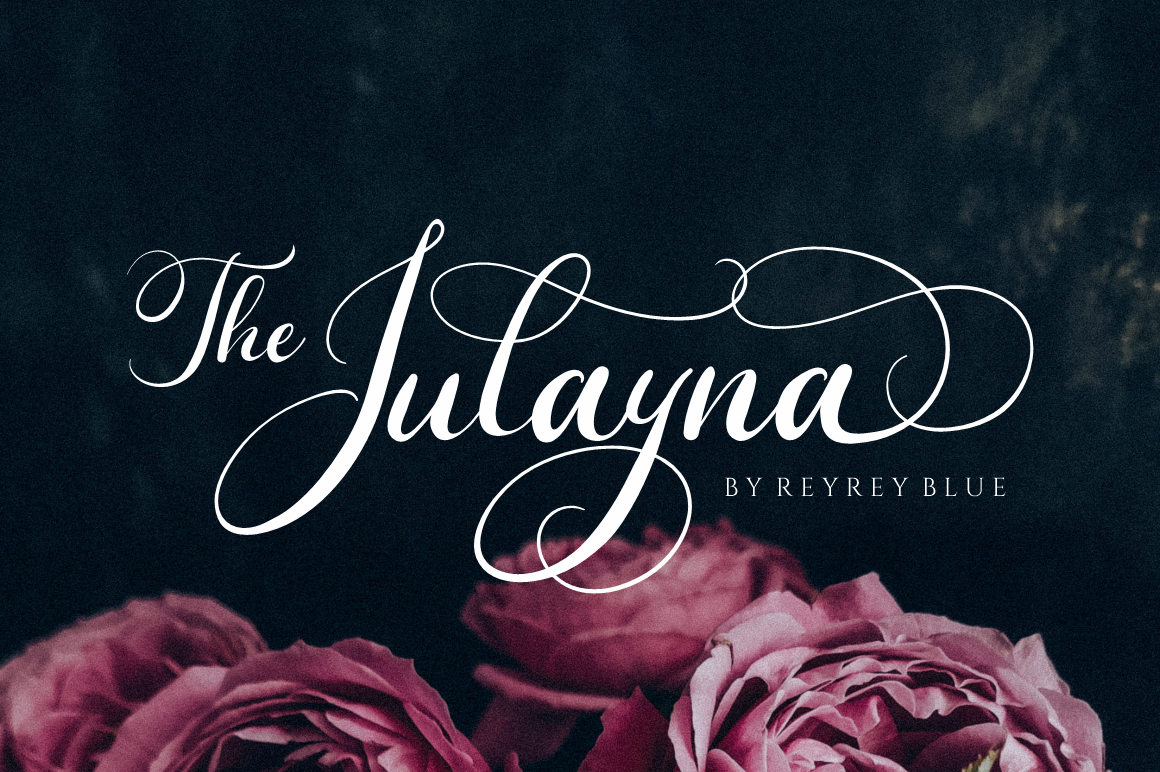
The Julayna Font – Download Grátis
A fonte “The Julayna Font” é perfeitamente adaptada para qualquer projeto que exija elegância e sofisticação. Ela se destaca quando usada para criar cartões de boas-vindas, embalagens de produtos, selos ou até mesmo logotipos inovadores. Este script meticulosamente elaborado não apenas reforça a mensagem do seu design, mas adiciona um toque refinado e autêntico. Seja você criando uma campanha de marketing envolvente ou simplesmente enriquecendo sua identidade visual com estilo, “The Julayna Font” é a escolha certa para destacar qualquer mensagem que desejar transmitir. Suavemente elegante e repleta de personalidade, esta font oferece uma maneira única de criar um design único e memorável. Seja qual seja seu projeto ou seu objetivo de comunicação, “The Julayna Font” tem o poder de se destacar e elevar sua proposta ao próximo nível.